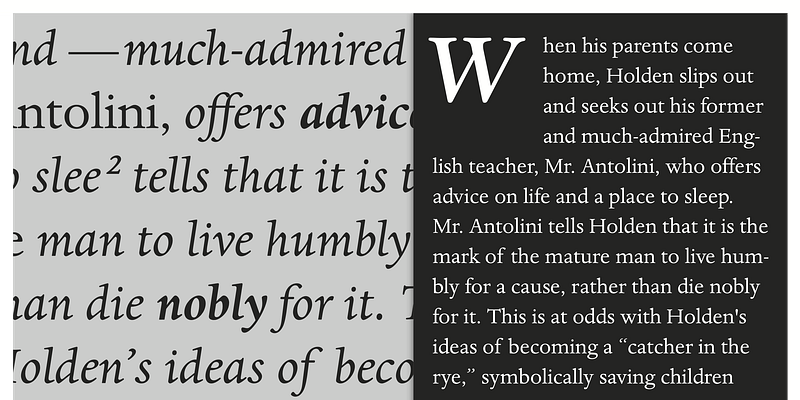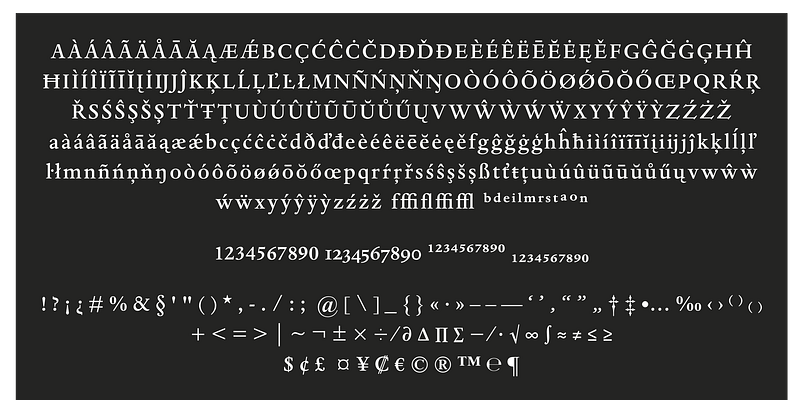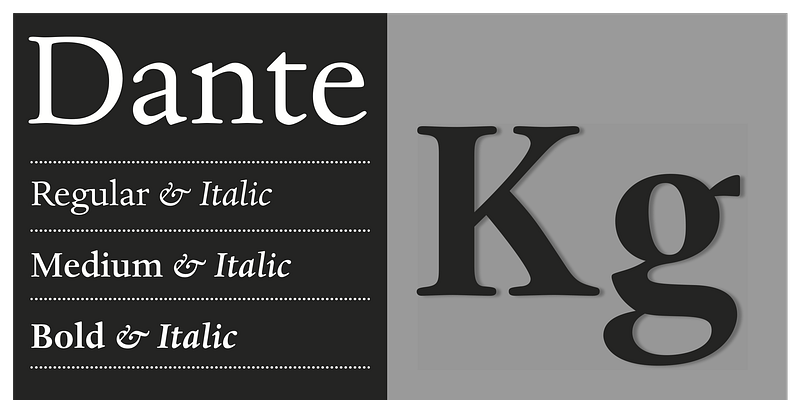
Dante wurde von Giovanni Mardersteig entworfen. Mardersteig begann mit der Arbeit an Dante nach dem Zweiten Weltkrieg, als die Druckerei Officina Bodoni wieder auf vollen Touren kam. Er schöpfte aus seinen Erfahrungen mit Monotype Bembo und Centaur, um eine neue Buchschrift zu entwerfen, deren Kursivschrift mit der Antiqua harmonierte. Ursprünglich von Charles Malin handgeschnitten, wurde Dante 1957 von Monotype für den mechanischen Satz adaptiert. Die neue digitale Version der Schrift wurde von Ron Carpenter von Monotype neu gezeichnet, frei von jeglichen Beschränkungen der Bleisatztechnik. Die Schriftfamilie Dante wurde 1993 in drei Stärken mit einem Satz Titelversalien herausgegeben. Dante ist eine wunderschöne Buchschrift, die auch in Zeitschriften, Periodika usw. gut zur Geltung kommt.